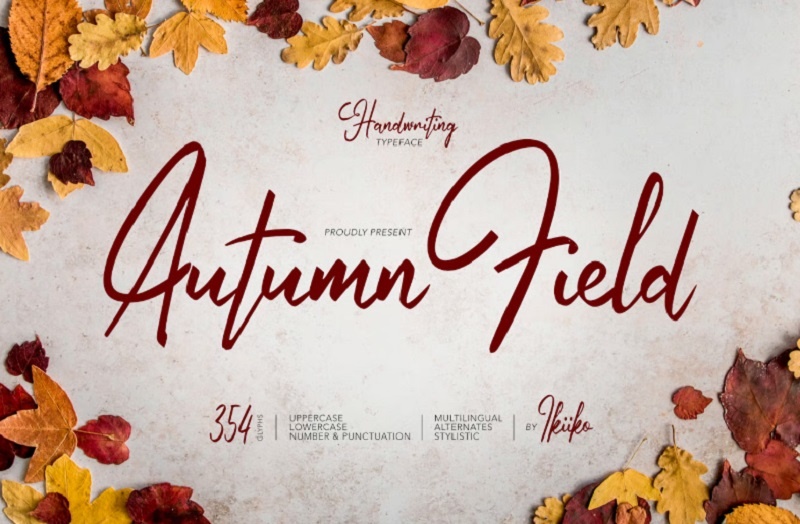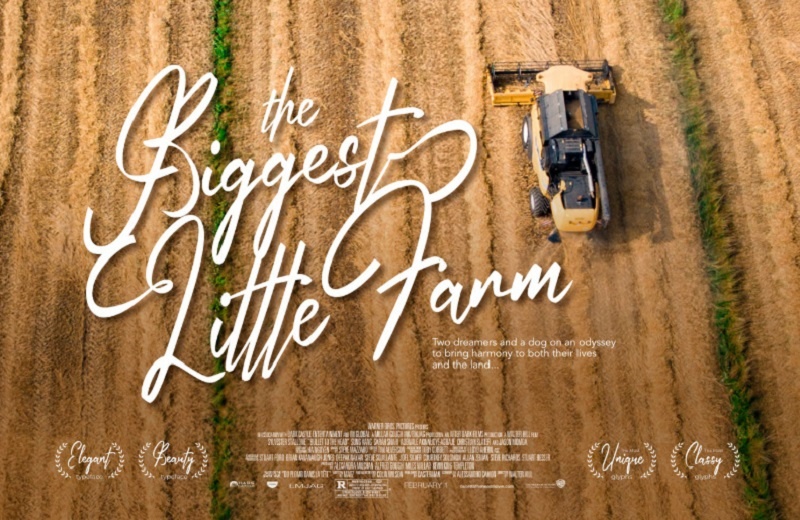
دانلود 5 فونت انگلیسی پاییز Autumn Font
فونت پاییز زیبا، مدرن و جدید شامل 5 فونت پاییزی در جی اف ایکس دانلود می باشد. این مطلب شامل دانلود فونت انگلیسی پاییز می باشد که می توانید برای طراحی های مختلف از آن استفاده نمایید. این فونت پاییزی برند و محصول شما را با ارزش تر نشان می دهد. در ادامه می توانید ویژگی ها را مشاهده و فایل اصلی فونت را از جی اف ایکس دانلود دریافت نمایید.
فونت انگلیسی پاییز
2- دانلود فونت انگلیسی پاییزی Thanks Autumn
این فونت انگلیسی پاییزی به سبک دست نوشته و دستخط می باشد. استفاده از این فونت زیبا، سبکی گرم و دلنشین به طراحی های شما می دهد. شامل فایل هایی با فرمت OTF، TTF، WOFF می باشد.
فونت انگلیسی به سبک پاییز Thanks Autumn
3- دانلود فونت انگلیسی پاییز Autumn Good
Autumn Good Font یک فونت مدرن و بسیار زیبا با تم پاییزی است. فونت انگلیسی پاییز Autumn Good مناسب برای نیازهای حرفه ای و برندینگ محصول، لوگو، هدر وبلاگ، پوستر، نواربندی، نامه، دعوت نامه، لوازم التحریر و غیره مناسب است و می تواند در طیف وسیعی از پروژه ها و رسانه ها استفاده شود.
فونت انگلیسی پاییز Autumn Good
4- فونت انگلیسی پاییزی Warm Autumn
Warm Autumn یک فونت زیبای پاییزی است. این فونت انگلیسی پاییزه برای هر پروژه مانند لوگو، طرح های پاییز، کارت تبریک و بسیاری موارد دیگر مناسب است. شامل فایل های otf .ttf .woff می باشد.
مجموعه فونت پاییز انگلیسی برای طراحی پوستر و شبکه‌های اجتماعی
5- دانلود فونت انگلیسی جذاب مخصوص طرح‌ های پاییزی
اگر در حال طراحی پوستر، کاور شبکه‌ های اجتماعی یا هر پروژه گرافیکی با حال‌ و هوای گرم و دلنشین پاییز هستید، این مجموعه می‌ تواند برای شما بسیار کاربردی باشد. در این بخش می‌ توانید دانلود فونت انگلیسی جذاب برای طرح های پاییزی را انجام دهید که فضای آرام و رنگارنگ فصل پاییز را به بهترین شکل منتقل می‌ کنند. این فونت پاییزی Autumn Field برای طراحی کارت دعوت، تایپوگرافی فصلی، بنرهای مناسبتی و حتی پروژه‌ های چاپی انتخابی حرفه‌ ای محسوب می‌ شود.
دانلود فونت انگلیسی پاییزی برای تایپوگرافی و پروژه‌های گرافیکی
✅ نام فونت 1 Autumn Unique Display Font
✅ نام فونت 2: Thanks Autumn
✅ نام فونت 3: Autumn Good
✅ نام فونت 4: Warm Autumn
✅ نام فونت 5: Autumn Field
✅ مدرن و زیبا جهت لوگو برند